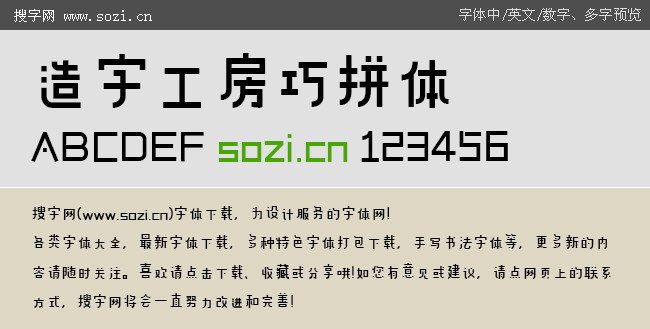
造字工房巧拼體
搜字網(wǎng)給大家提供一款造字工房巧拼體中文字體下載,造字工房巧拼體是一款字形大小錯落、疏密得當,簡潔方整卻又毫無刻板拘泥之感,極富變化的同時卻無嬌柔造作之姿,筆畫粗細均勻,點處理為方點,天真有趣、憨態(tài)十足。此款字體適用于兒童讀物、報刊雜志標題、廣告設(shè)計等應(yīng)用。(本字體為個人非商用版,如需要商用請聯(lián)系官方購買版權(quán))